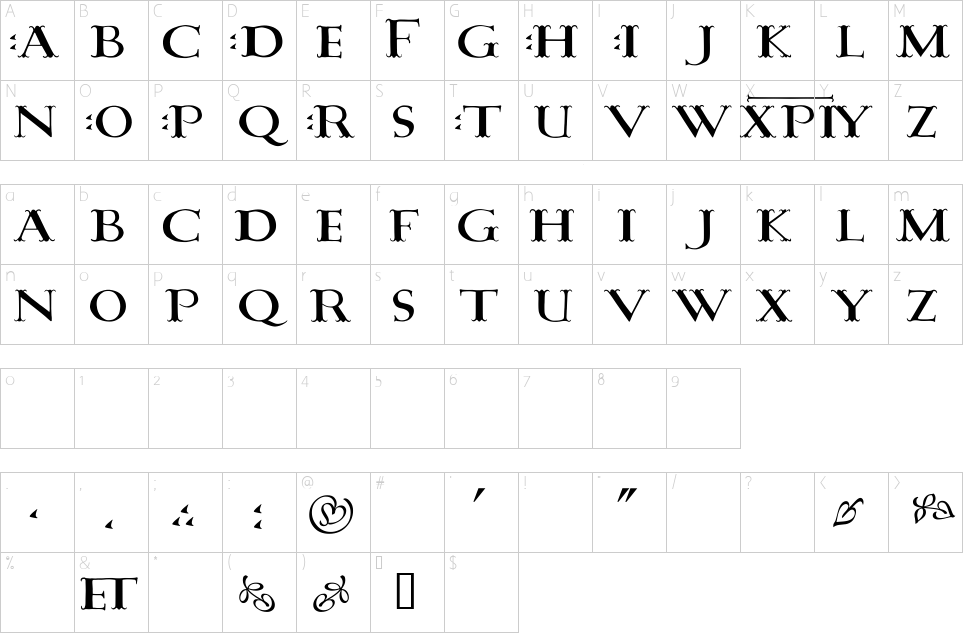
A Damasus LDR é uma elegante e sofisticada fonte que se destaca na categoria de fontes gratuitas. Desenvolvida pelo designer Luigi Della Rosa, ela foi projetada para oferecer um toque contemporâneo à sua escrita, sem perder o charme das fontes mais tradicionais. Seja você um profissional ou uma pessoa que simplesmente gosta de criar belos documentos digitais, Damasus LDR é perfeita para quem procura uma opção versátil e moderna. Esta fonte foi baixada 12.713 vezes por usuários apaixonados em todo o mundo, um número que reflete seu valor como uma fonte de alta qualidade disponível livremente. Se você está procurando por uma solução confiável para adicionar um toque único a seus projetos digitais, Damasus LDR é a escolha certa. Descubra agora a beleza desta fonte e experimente sua versatilidade imediatamente.